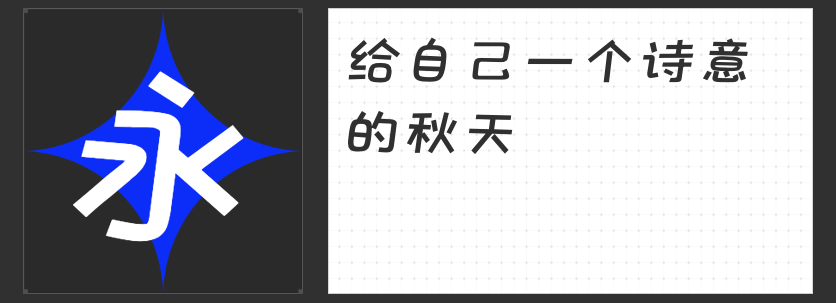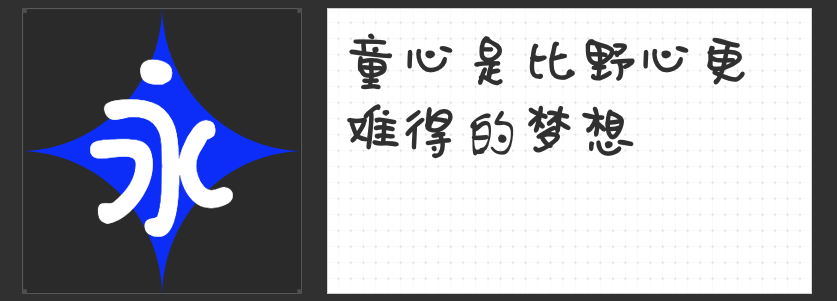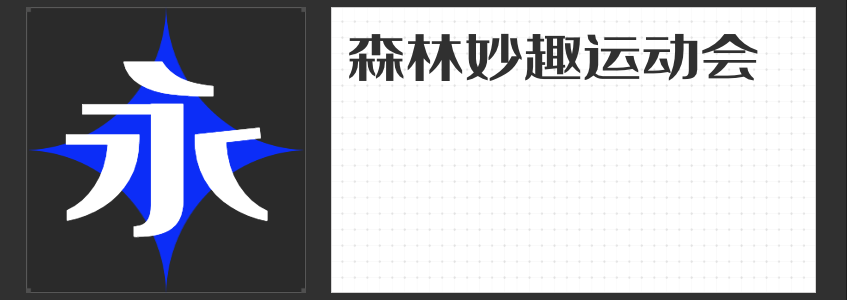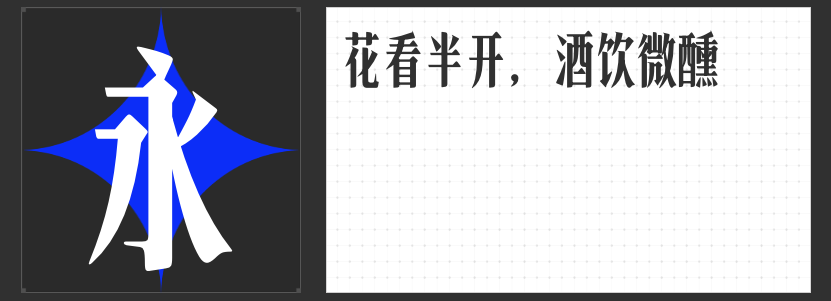
美妆宣传新风尚:四款精选字体点亮产品魅力
在美妆产品日新月异的今天,如何通过视觉设计吸引消费者的目光成为品牌竞争的关键。字体作为设计的重要元素之一,其选择直接关系到产品包装与宣传的成败。今天,我们特别推荐四款适合美妆产品设计的字体,它们各具特色,定能为您的美妆品牌增添无限魅力。
1.也字工厂港风宋体
这款字体以其瘦长的外形和纤细的笔画,营造出浓郁的复古氛围。横竖粗细对比鲜明,仿佛将我们带回了那个风华绝代的港片时代。它特别适合用于复古风格的美妆产品包装,让每一款产品都散发出独特的怀旧气息。
2.励字魔方黑简
现代感与未来感并存,这款字体字形方正、简洁无装饰,横竖笔形粗细对比强烈,方头方尾的笔形设计更显干练。它适用于追求时尚与前卫的美妆包装设计,能够瞬间提升产品的科技感与未来感,吸引年轻消费者的目光。
一款充满趣味与可爱气息的字体,笔画整体向右倾斜,营造出一种轻松愉悦的氛围。它非常适合用于可爱风格的美妆产品宣传,无论是海报、广告还是社交媒体推广,都能让您的产品瞬间成为焦点,吸引更多年轻女性消费者的喜爱。
4.小豆岛默陌乐童简
这款字体以其独特的儿童字结构和稚拙的笔画风格脱颖而出。上松下紧的结构设计让字体看起来更加活泼可爱,宽细一致的笔画则增添了几分纯真与无邪。它非常适合用于可爱风格的美妆产品包装设计,让您的产品在众多竞品中脱颖而出,成为消费者的心头好。
四款字体,四种风格,总有一款能够满足您美妆产品宣传设计的需求。选择适合的字体,让您的美妆产品在市场中熠熠生辉!